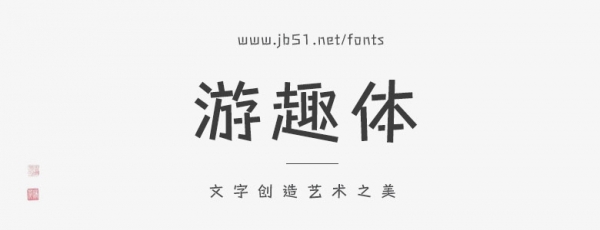
游趣體因筆形像筆桿一樣以直線設(shè)計(jì),而被視為一款既可愛調(diào)皮,亦有田園寫意風(fēng)格的字體,本人基于 Fontworks 出品的日文字體ステッキ / Stick 擴(kuò)充、調(diào)整字形,并編輯、適當(dāng)增加 OpenType 特性,以滿足簡體中文的使用需求。
補(bǔ)字計(jì)劃
簡體部分
目標(biāo)字匯①范圍內(nèi)修改 G 形②;
增補(bǔ)原字庫中含有的繁體字對應(yīng)的簡化字;
義務(wù)教育語文課程常用字表 3500 字;
GB/T 2312-1980 漢字部分 6763 字;
通用規(guī)范漢字表 8105 字;
現(xiàn)代漢語通用字表 7000 字;
按需添加一些表外字,參照「霞鶩開源字體外字初步整理一覽表」第一部分。
① 包括《義務(wù)教育語文課程常用字表》(以下簡稱《義務(wù)教育常用字表》)、GB/T 2312-1980、《現(xiàn)代漢語通用字表》《通用規(guī)范漢字表》。
② 修改范圍包括《義務(wù)教育常用字表》、GB/T 2312-1980、《現(xiàn)代漢語通用字表》《通用規(guī)范漢字表》,部分字形差異視為設(shè)計(jì)特性,不做修改,如「厶」「幺」「亥」等字。
繁體部分
由于該字體目前定位仍以簡體為主,目前無對原字體包含的繁體部分增補(bǔ)及修改的計(jì)劃。